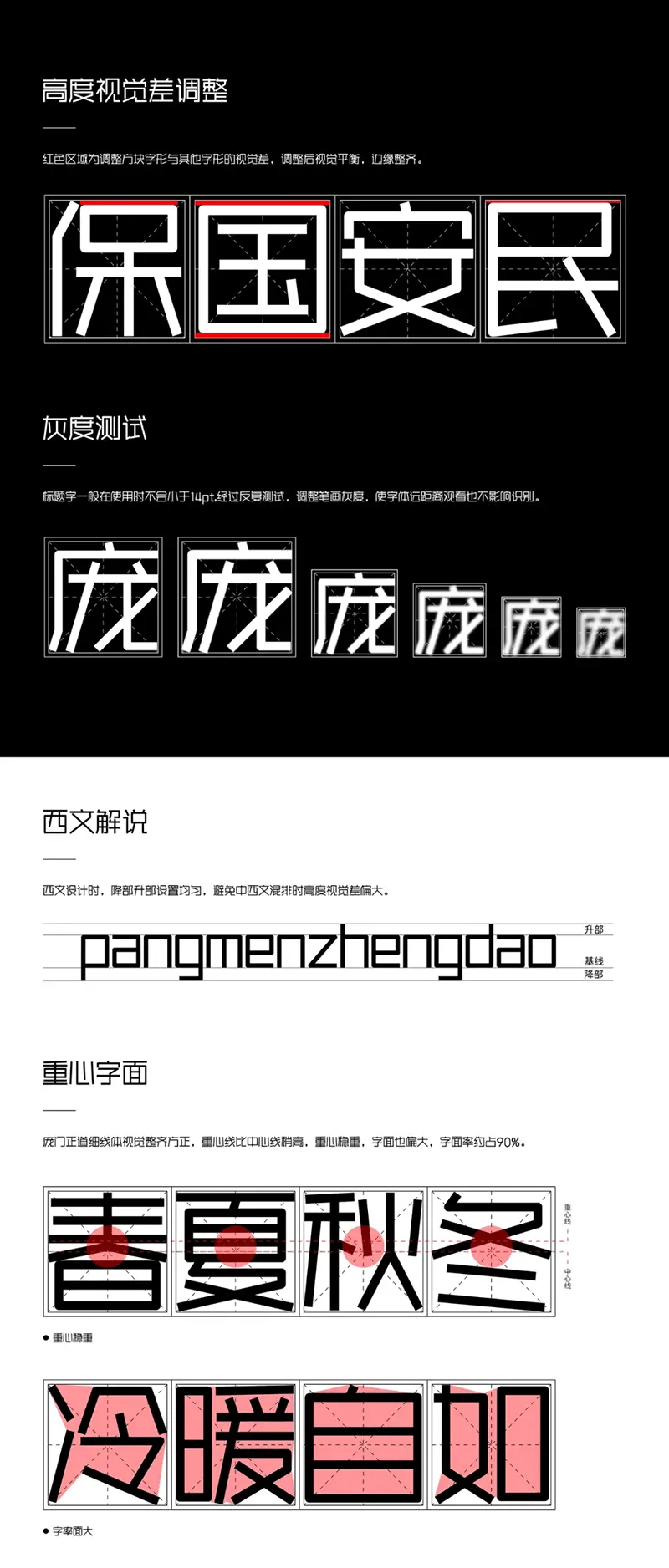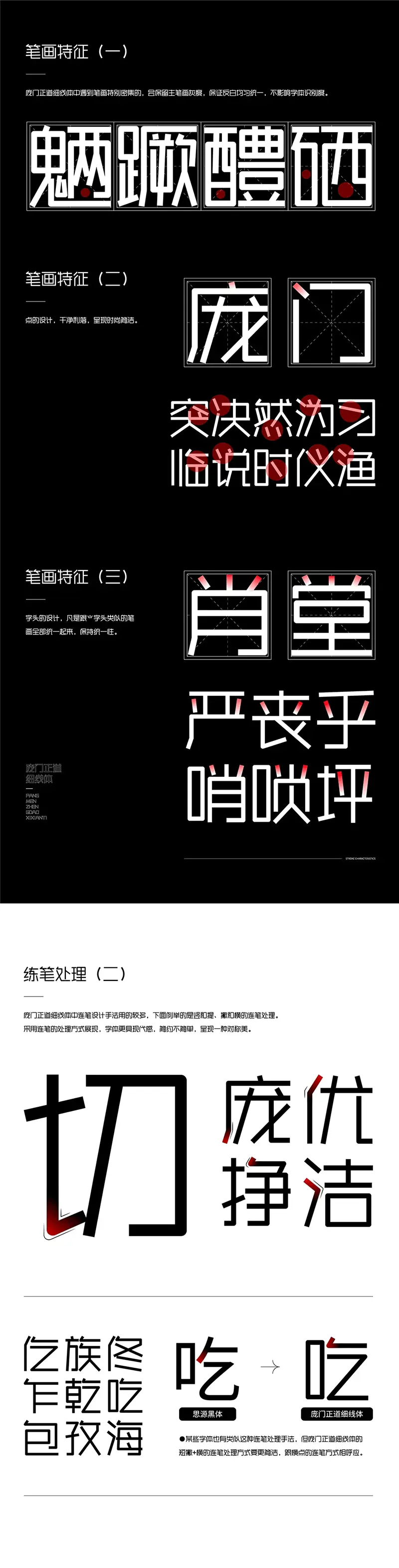
龐門正道的第八個年頭,邁過今晚,就是第9年。人生有多少個8年?我不知道。我還能不能堅持寫到下一個8年?我也不知道。但是我知道一個8年,可以做很多有意義的事情。就如2019年,我就和胡曉波工作室達成了合作,開發一款全新的字體,雖然我的計劃是免費商用,但是胡曉波工作室是養著二三十設計師的商業機構,不可能說讓他免費給我做,所以這次是按照他的商業報價後的友情折扣給我製作。多少錢就不說了,目前的商業品牌字庫是30萬一款,我花了同樣不止十萬就是了。
2020年其實已經交付,但是那時候我爸的那款字體也在同期製作,無暇接應那麼多,所以這一款就安排在2021年的12月24日,8週年的時間發佈。
這很可能是我發佈的最後一款字體了。
為甚麼可能是最後一款?
今晚,讓我再開心多一次。也讓大家開心多一次。全新龐門正道系列字體,龐門正道細線條,登場!